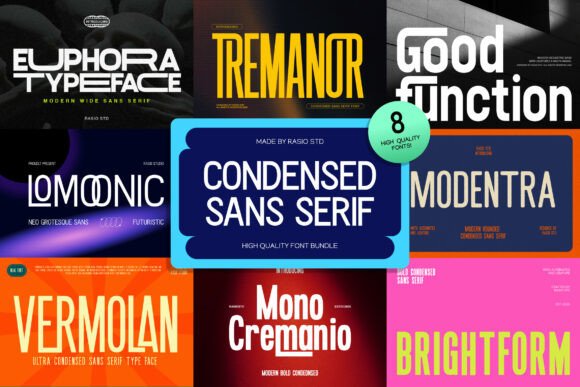
Condensed Sans Serif Bundle
قد يكون العثور على عناصر التصميم المناسبة أمرًا صعبًا، ولكن Condensed Sans Serif Bundle يقدم مجموعة استثنائية ترتقي بعملك على الفور.
سواء كنت تقوم بإنشاء منتجات الطباعة عند الطلب أو دعوات الزفاف أو رسومات وسائل التواصل الاجتماعي، فإن Condensed Sans Serif Bundle هو الخيار المثالي.